如何“假装”很懂字体?除了衬线和无衬线,这些“术语”先入门
导读:人文主义、怪诞风格、几何风格……看似抽象的字体风格概念,实则延展出鲜活的视觉特点。本文聚焦于 13 款经典西文字体风格,汇总丰富细节,构建关于字体风格的综合视野。
历史上有许多字体分类体系,有些基于字体的历史时期,有些基于字体的视觉特点,有的则兼顾二者。比较著名的分类方式包括:
- Vox 分类系统:曾经是国际字体协会(ATypI)官方标准,是一种混合了历史和视觉特征的分类方法。
- 英国标准字体分类:Vox 分类系统的简化版。
- Gerrit Noordzij 的字体理论:认为所有字体都可以追溯其书写工具从而做出分类,从书写中构建认知,弥补了仅按照历史时期来划分的缺陷,但也遗漏了给定维度之外的情况。
下面,就让我们从经典字体风格的历史源泉出发,着眼视觉特点分析,感受西文字体的微妙细节。
1 衬线字体
1.1 人文主义衬线体(Humanist Serif)
最早的罗马体源于书法,字型基于用扁平笔刷书写的正式字体。人文主义一词最早用于描述衬线体,但如今也出现了人文主义无衬线体。
字体特点:倾斜角度大,x 字高较小,笔画粗细对比度低,小写字母 e 的横线笔画倾斜,呈现自然书写运笔的痕迹。代表字体:Centaur、Guardi、Lutetia、Stempel Schneidler
1.2 Garalde
Garalde 是由 15 世纪末至 18 世纪间最著名的两位字体设计师名字组合而造出的单词,分别是法国字冲雕刻师 Claude Garamond 和威尼斯印刷匠 Aldus Manutius。Garalde 字体由人文主义衬线体发展而来,但仍未褪去手写气息。
字体特点:比例良好,粗细对比更明显,倾斜角度适中,衬线形状更清晰,小写字母 e 的横线笔画水平。代表字体:Garamond、Bembo、Janson、Palatino、Galliard、Caslon、FS Brabo
1.3 过渡风格(Transitional)
17 世纪末,法国国王路易十四想要更新皇家印刷局的印刷机,寻找 Garamond 的替代字体,与同时期欧洲别国竞争印刷业的发展。于是,他委托法国科学院设计出了一款新字体 Roman du Roi – 86,这款字体基于严格的网格、数学和工程系统设计。这一时期的著名字体设计师有 John Baskerville、Simon Fournier 和 Christophe Plantin。过渡风格的字体也被称为"realist",源自于 Plantin 为西班牙国王菲利普二世设计的字体,这个词在西班牙语中意为"royal"(皇家,与现实主义无关)。
字体特点:笔画对比度较前两种风格的字体更强;粗细对比逐渐有别于书法,轴线接近垂直;衬线更平滑,细节处理非常精细。如果你把它们看作是老式字体和现代字体之间的"过渡",就很容易识别出过渡风格的字体。代表字体:Baskerville、Fournier、FS Neruda、FS Sally、Joanna、Melior
1.4 Didone
Didone 一词取自铸字匠 Firmin Didot 和 Giambattista Bodoni 名字的组合,这种在当下看来仍旧十分前卫时尚、备受时尚杂志青睐的字体实际上在 18 世纪中期就出现了。他们二人技艺精湛,彼此切磋,促进了字体设计、字冲雕刻技术和印刷的发展。
字体特点:笔画对比度极大。前几组衬线字体风格受到平头笔的影响,该字体则受到尖头笔的影响,以 90 度的角度书写,因此笔画水平且纤细。字体轴线完全垂直,衬线与笔画没有圆弧过渡。代表字体:Didot、Bodoni、FS Ostro、Walbaum
1.5 板状衬线体(Slab Serif)
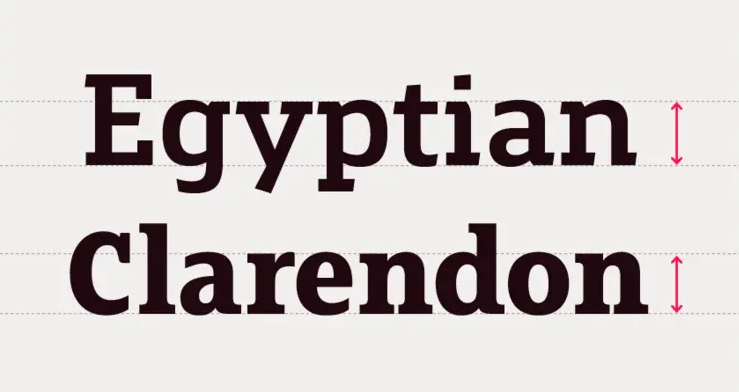
板状衬线体还可以称为 Mechanical / Mechanistic(机械风格体)、Antique 或是 Egyptian(埃及体)。由于其衬线多为厚重的矩形,能够有效引起注意,因此设计之初多用于广告、海报和大尺寸的媒介。它们彰显了 19 世纪初工业革命的精神,为大型展示用途而生。板状衬线体可以再细分成没有圆角过渡的衬线(通常被称为 Egyptians)和带圆角过渡的衬线(被称为 Clarendons 或 Ionics)。
字体特点:小写字母的 x 字高较高,笔画横竖粗细较为一致,尽可能地占满空间。除了衬线上的区别外,Egyptians 风格字体通常更加板正机械,而 Clarendons 则更为精致柔和。代表字体:Memphis、Rockwell、Clarendon、Sentinel、FS Silas Slab、FS Clerkenwell、FS Rufus
2 无衬线字体
2.1 怪诞风格(Grotesque)
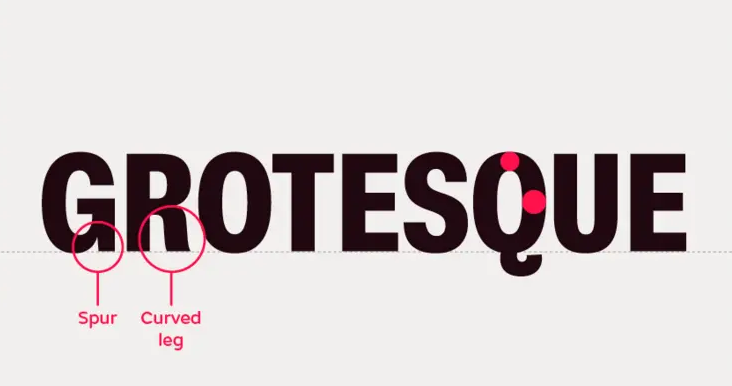
怪诞风格是起源于 19 世纪的一种无衬线字体,是最早的无衬线体之一。之所以名为"怪诞",是相较于当时占据主导的衬线体,去除了衬线的字体被认为是古怪、反潮流的。因此,Grotesque typeface 现在也被译作"早期无衬线体"或"旧式无衬线体"。怪诞风格字体降低笔画对比度,以用于标题和广告,许多作品仅使用大写字母;但随着怪诞风格的发展,我们也首次看到了无衬线小写字母。
字体特点:笔画粗细对比不一,时而适中时而强烈,与书写字的笔画对比逻辑缺乏关联。圆形或者带有弧线的笔画较方,收笔往往是水平或内卷的。"G"的竖笔像一根刺,"R"的最后一笔有时会有弧度。代表字体:Bureau Grot、Franklin Gothic、FS Meridian、Knockout、Venus
2.2 新怪诞风格(Neo-grotesque)
作为怪诞风格的延续,新怪诞风格字体中有许多时至今日仍广受欢迎的字体,如 Helvetica 和 Univers。不同于仅为标题和广告而生的怪诞风格,新怪诞风格注重简洁性、易读性和广泛的适用性。Helvetica 和 Univers 也是最早包含了多款字重与字宽的字体家族,适用于多种用途及尺寸。
字体特点:与怪诞风格相比,笔画对比度更小,字母的比例与形状更一致;字母"G"通常不带字刺,小写字母"g"通常是单层的。代表字体:Helvetica、Univers、DIN、Bell Centennial、FS Elliot、FS Industrie、Folio
2.3 几何风格(Geometric)
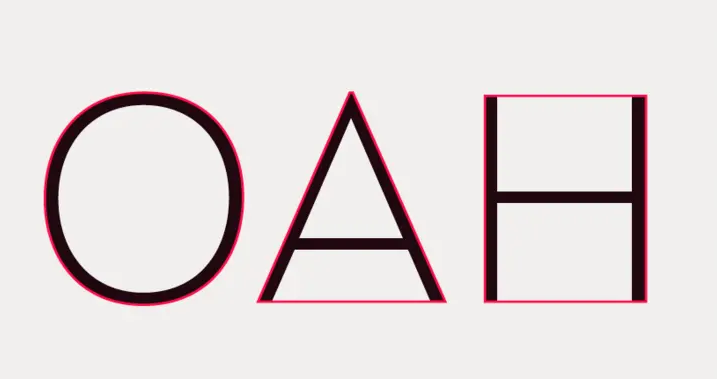
顾名思义,几何风格的字体通常由简洁的几何形状构成。这类字体的设计看起来简单,实际上需要经过大量细微的视觉调整,使字形看起来干净而线性。几何风格字体的设计思路之一起源于 20 世纪 20 和 30 年代,利用一系列的几何形状来实现字母比例的变化;另一种思路则是受到工业中用钢板、金属或塑料切割出简化字母的启发,采用重复的几何元素来构建字母,减少比例变化,统一外观。
字体特点:笔画粗细对比通常很小,结构由圆形、方形、三角形等基本几何形状的重复元素组成。最常见的是单层字母"a"和"g",呈现极简的几何感。代表字体:Bank Gothic、Erbar、Eurostile、FS Lucas、FS Dillon、Futura、Kabel
2.4 人文主义无衬线体(Humanist sans)
如前文所述,人文主义衬线体深受平头笔书法的影响,人文主义无衬线体也有类似特征。字母比例基于经典的罗马体,这使得人文主义无衬线体比怪诞风格和几何风格的无衬线体更适宜阅读。
字体特点:笔画粗细对比较小,但依旧可以分辨出来;笔画带有书写的角度,但不像人文主义衬线体那样明显。书法还影响着字母的结构、开放的字怀、笔画之间的连接角度,以及常见的双层小写字母"a"和"g"的选择。人文主义无衬线体经常会配备真正的意大利斜体,而非机械化拉伸正体版本。代表字体:FS Millbank、FS Irwin、FS Siena、Gill Sans、Johnston、Scala Sans
3 其他类别
3.1 书法风格(Script)
书法风格字体基于手写体,通常可以根据不同的书写工具加以区分,如毛笔、马克笔或尖头笔等;风格可以像古典书法那样非常严肃,也可以轻松随意。
字体特点:字母之间通常带有连笔,具有一定的倾斜角度,如同行书。很多书法风格的字体要求设计师为每个字母绘制多个字符形,以此来复现手写字母的多变与灵动。代表字体:Zapfino、Bickham Script、FS Shepton、FS Sammy、Mistral、Snell Roundhand
3.2 图形风格(Graphic)
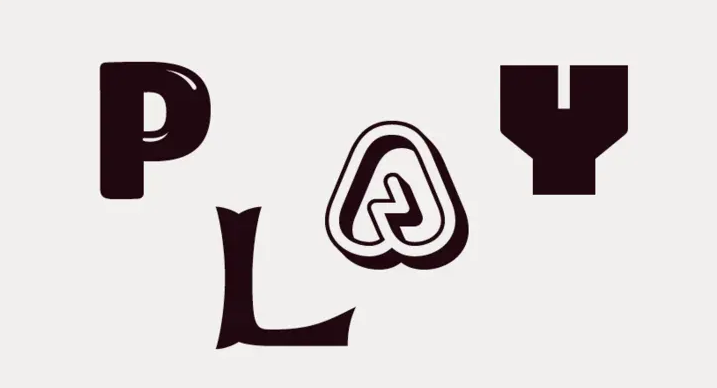
图形风格涵盖几乎所有其他分类没有的标签,如装饰、分层、纹理、镂版、阴影等。如果你无法确定某字体的风格,它看上去不基于手写和几何绘制,而是像随机形状组合或是特效制成,那么它大概率是图形风格字体。
字体特点:通常用于标题字,尺寸较大,能够吸引眼球。代表字体:Banco、FS Conrad、FS Kitty、FS Pele
3.3 哥特体(Blackletter)
这一字体风格起源于 15 世纪的德国印刷匠 Johannes Gutenberg,最早的哥特体以手抄本字形为蓝本。Gutenberg 的金属活字发明促进了哥特体的传播与使用,但哥特体最终被更易读的衬线体所取代。如今,哥特体主要出现在啤酒标签、重金属和嘻哈音乐的视觉设计上,有时也被称为破笔体或黑字体。你或许会把哥特体误认为图形或书法风格字体。事实上,哥特体也是用平头笔书写的,只是运笔方式不同,书写角度为 45 度。
字体特点:字母造型主要由粗直线与细斜线变化构成。字母较为狭长,使文本看起来非常浓密和锐利。代表字体:Fette Fraktur、Goudy Text、Linotype Textur、Notre Dame、Old English
3.4 雕刻风格(Incised)
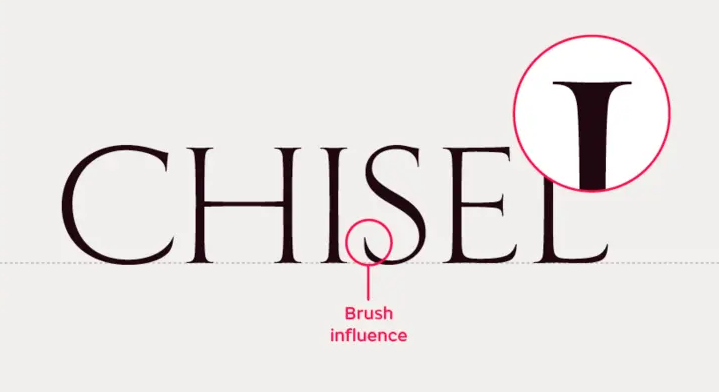
该字体风格也被称为 Glyphic,灵感来自石头雕刻字,而非书法字。很多雕刻风格字体都参照了古罗马铭文,并且很可能只有大写字母;例如 Trajan 这款字体,就是依照了图拉真石柱(Trajan column)上的字母设计。也有很多雕刻风格字体并非对古典形式一板一眼的复兴,而是设法将雕刻特征融入到小写字母中,使用外扩的笔画末端和书法结构。雕刻风格字体有时可能会被和基于书法的衬线体混淆,但它的衬线是凿刻的痕迹,而非设计装饰元素。
字体特点:雕刻风格字体的衬线通常更小,有些仅出现在笔画末端,呈喇叭状开口。字母比例沿袭经典的罗马正体。代表字体:Trajan、FS Rome、Albertus、FS Benjamin
4 结语
诚然,字体设计是一门存在诸多变量的复杂学科,当下的字体实践总会不断超越,几乎不可能设计出一套包罗万象、尽善尽美的分类系统。
但接触字体设计的历史,理解某种风格的历史内涵或视觉特征,将有助于设计师在选择或匹配字体时更游刃有余,对与客户沟通选定字体、讨论字体定制方案或是丰富设计视野都大有裨益。
* 本文编译自 Krista Radoeva 的 A GUIDE TO TYPE STYLES。